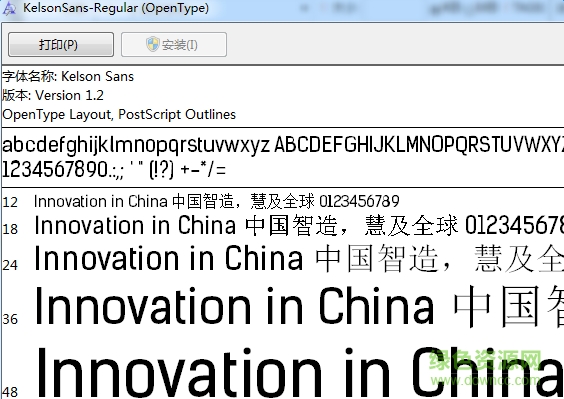
KelsonSans英文字體
KelsonSans字體是一款極具個(gè)性的中文字體,文字排版、海報(bào)廣告設(shè)計(jì)、藝術(shù)設(shè)計(jì)等方面都可以使用,有需要的朋友不要錯(cuò)過(guò)了,歡迎大家來(lái)綠色資源網(wǎng)踴躍下載哦!
KelsonSans是非常具有個(gè)性的英文字體,改字體字型非常中肯,有喜歡的朋友可以來(lái)綠色資源網(wǎng)下載使用!